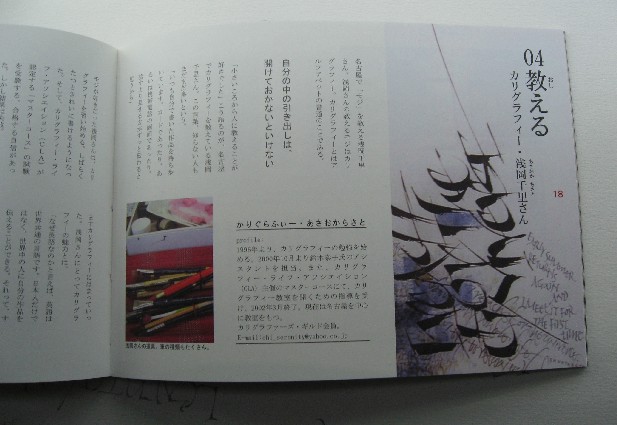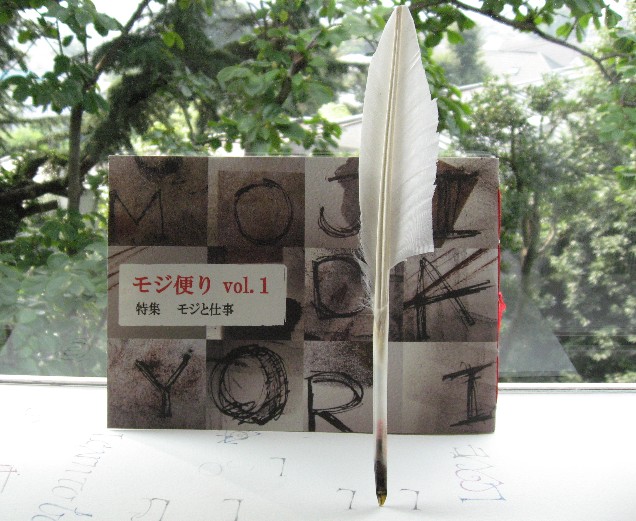
モジ便り
先週は、あるものを楽しみに待っていました。
それは「モジ便り」。
何か素敵な響きですね〜。
この本は、モジ好きの猿田彩さんという方が個人で作っている本なのです。文字に魅せられて、文字に関する仕事がしたい…という気持ちが「モジ便り」という形になったそうです。
表紙から中身まで、全て個人で取材、編集、デザイン、赤い糸で綴じたのもご本人!
輝かしい第1号の内容は、「書く」「売る」「デザインする」「「教える」の4つの枠を、仕事という視点でインタヴューを行った記事が載って
います。
文字好きなら興味深々の内容が並んでいます。
猿田さん自身が、いかに文字に対して愛情を感じているのかがわかる手作り本です。
今回は、カリ人浅岡千里さんの記事も載っています。
以前、mojitor-sさんが紹介されていた方ですね。
様々な地域で文字に携わっている方の様子を知ることができて
興味深いです。
「モジ便り」はお取寄せで待っている感じ…。
届くまで楽しみ〜。届いたら、すぐに中身を「いただきます!」
「やっぱり、待っていた甲斐があった美味しさ」
読み終えた後は、お茶席ならば「結構なお手前でした…」満足感にお腹いっぱい、頭もいっぱい
です。堺さんなら…?「星3つです!」
原稿用紙
先日、御茶ノ水へ行った時に入ったお店に、いろいろな種類の原稿用紙が売られていました。
原稿用紙というと昔小学校の時に作文を書く時に使ったなぁ、と懐かしくなりました。でもよく見ると、いろいろな種類があって、こだわる人はきっと選んで使うんだろうなぁ、と興味深く物色しました。
自分の名前入りというオーダーも出来るようでした。それって小説家の人が注文するんでしょうねぇ。でも今時パソコンが主流でしょうから、手書きの人が使うこういう原稿用紙はあまり売れないのかもしれませんね。
なんだかとても書き味を試してみたくなって、ふふふ!買ってみましたよ〜。100枚入っていて800円。どんどん練習に使うには惜しくないお値段。
やはりこの原稿用紙のクリーム色には、ウォルナッツインクのセピア色が似合いますね。上部にある升目のない部分のスペースが使えます。本来は校正の書き込みに使うのかしらん?
私が購入したのは、舛屋という紙屋さんの満寿屋(ますや)というブランドのものでした。浅草にある明治15年創業のとても古いお店の様です。
満寿屋の原稿用紙
舛屋
HPによると、川端康成、司馬遼太郎、井上靖、大江健三郎、三島由紀夫、吉川英治、吉村昭、瀬戸内寂聴、浅田次郎、などなど・・・・・・・。日本を代表する様な作家たちが愛用しているとか。すごいですね。
「ペン先を傷めぬ柔らかなタッチ、ユニークな升目、邪魔にならない色合い」と書いてあります。きっと長く使っていくと他とは違う使いやすさや味わいがあるのでしょうね。
関東地区だけでなく、関西や北海道、九州など全国で取り扱っているようです。
スラスラ書いてみたい人には、最適かも。お試しあれ〜
DERWENT METALLIC
ダーウェントのドローイング用の色鉛筆は素敵です。
以前、神戸のSさんがイギリスで入手したというのを使わせて頂いたことがあります。それぞれの色についた名前も素敵な響きでした。
国内で手に入れるのは難しいのかもしれません。
先日、美篶堂のショップでダーウェントのメタリックカラーが単品で売って
いたので、買ってみました。セットだと12色あるらしいですが、ショップでは5〜6色が置いてありました。
メタリックというからには、やはり暗い色の紙に書くと発色がいいのかな?
と思い、黒い紙に書いてみました。
さすがに目だっていますね…。ウエットにもドライにも使えるので、
脇役でも活躍しそうです。光沢が強いし、色がきれいです。他の色も
欲しい…。
白い紙の上でも、きれいに発色しています。
書いた感触では、goldが他の色より硬い気がしました。他の色pink, blue, pewter, silverは柔らかく滑らかでした。ドローイング用らしいので、普通の水彩色鉛筆より書きやすいかもしれません。
green とかyellowもあるようなので、それも使ってみたいです。
試し書き、描き…。
難しいことを考えないで、手を動かしているのが一番楽しいですね…。
コラージュのその後
先日作ったコラージュ用の紙がついにバラバラの残骸になりました。ということは、何かが出来たということです。
ドローイングと言う名前のクラスですが、何かを写生すると言う様な内容では全然なく、実に創造性を広げてくれる素晴らしいクラスなのです。
今回も、本当に楽しい内容でした。
そして出来たのは今のところこれとこれ。
他のメンバーの方たちのも是非紹介したい位、とても完成度の高いものが出来上がりました。
これは白黒のみの方ですが、実はカラーのも作ったのです。
それはまたいつかご紹介するとして、これら白黒のものにもまだもう少し書き足す事も考えています。やめた方が良いかなぁ・・
一緒に参加しているmojitor-hさんはコラージュにトラウマがあるとおっしゃっていましたが、それを打ち破って、素敵なカードも作っていました。一見の価値ありです。
コラージュは薄い紙の方が適していると思っていましたが、そうでもないんですね。
厚紙だと貼ったところにすこし影ができて立体的になり、非常にいい感じです。
講師の羽賀洋子先生の絵本の原画も見せて頂きました。コラージュです。印刷にはない色とテクスチャーがきれいでしたよ。
次回は「スピードの違う様々な線を使って描く」という内容です。
面白そう!
色をまぜまぜ
子どもが絵画教室に通い始めました。先日「50色つくる」という課題をみんなでやってみたそうです。
その塗り塗りしたものを持ち帰ってきたのですが「50色なんてそんなにたくさん作れなかった」ということでがっかりしていました。
まあ似たような色もあるものの1ページ分は作ることができたし、よかったじゃないの、と慰めて。
色としては私好みの色なので「いい色だねえ、あらー、この色は大好き」とほめて、本人満足。
混色するのは難しいけれど、子どもも大人も楽しいですよね。この色とその色とでどんな色ができるかなあ?なんて試してみるのはいいもんです。色見本をきちんと整理しておくとよいのですが、なかなかできないままに日が過ぎていってしまいます。
昔Denys Knightのワークショップで作ったガッシュの混色見本は今でも重宝しています。このワークショップのときにNaples Yellowを知って、手持ちの色に片端から混ぜて試したことを思い出します。透明水彩での混ぜ混ぜも飽きずに続けられる作業です。
秋の夜長にゆっくりやってみたいのですが、夜は早く寝てしまうので・・・途中で起きようと目覚まし時計をセットしているのですが
気がつくといつも朝、なんですよねえ。
週末くらいは夜更かししてみようかな。
栗ばっかり!
秋になると栗に憧れます…。栗!栗!栗!
面倒くさがりな私は栗剥きは苦手…というか、手は出しません。
だから、和菓子屋さんで剥かれた栗が形になっているのを見ると
嬉しくなり、買ってしまいます。
大福なんかは、秋の名月をお菓子の中に隠してあるみたいで、
栗が顔を出すと幸せな気持ちになります。くり〜。
まずは、「たねや」さん。一口サイズの上品な品揃い…。
白いまん丸したのは、「近江栗大福」(3個入り630円)。ど〜んと大きな栗が!存在感ありありです。周りのお餅も嬉しくなるぐらい美味しい!
茶巾しぼりの形をしたかわいいのが、期間限定?「さいぎぼく」(1個315円)です。こちらは少々高級な価格ですが、蒸されてまっとり(まったりとはちと違います)した口あたりが〜顔がほころびます。
昨日は、白山でデッサンのクラスがあったので、おやつにと
お取寄せした「栗抹茶大福」を持参。抹茶の香りがする餡で包まれた栗がここにいます〜。
伊藤久右衛門http://www.rakuten.co.jp/itohkyuemon/
Mさんが、自家製マロングラッセを持ってきてくれて、蜂蜜を使ってあるということで、何とも円やかに仕上がっていました。
あまりに魅力的だったので、写真撮るのを忘れてすぐに食べてしまいました〜しまった…。
栗の表示も楽しいですね…。
漢字だと視覚がすぐに味覚につながるようです。
左が、「たねや」さんの箱についていた「栗マーク」で
右が、「伊藤久右衛門」さんの箱についていた
「栗マーク」です。
タ〜ンと栗を頂いたあとは、残ったクロモジで記念の「栗マーク」
を描いて思い出に残します。
みなさんのお勧めの「栗お菓子」は何ですか?教えてくださいね。
2006年10月25日
平筆のイラスト
先日、折り形の本をアメリカの友人に送ったところ、お礼のカードと手紙が届きました。
折形レッスン―美しい日本の包み方内容は日本語で書いてありますが、折り線の種類と意味さえわかれば、器用な人なのできっと大丈夫だろうと、メモ書きだけ入れて送りました。
返事には、大丈夫だったと、書いてありました。さすがです。
お礼の手紙とカードは、得意の平筆によって花の絵が書いてありました。きれいですねー。どうやって平筆を使ったのか知りたいものです。花びらは平らに平筆を置いて、内側へシュッとかすれた線を出して書いているだけかもしれません。 今度試してみましょうね。
さて、お礼にということで彼女が取ったベティロークというカナダ人のワークショップのテキストが入っていました。私もアメリカにいる時に何度か彼女のクラスを取りましたが、平筆のマスターです。いろいろなアイデアと形がダントツに面白いのです。
特にこの部分、ハロウィーンのジャック-オ-ランタンとクモとタコみたいなゴーストが可愛いでしょう!?
ますますバージョンアップしていて、楽しくなります。
きっと描けないものなどないでしょうね〜〜。
よく見たら上の部分にA〜Zまで書いてありました。
これでけでもなーんて素敵!
2006年10月22日
韓国和紙
サキチさんに韓国和紙をお土産に頂きました。
韓国なので和紙ではなく韓紙と言うのだそうです。印刷(版画のような感じ)ですが、風合いがあってとてもイイ感じなのです。
残念ながら私はハングルは読めないので、この方向で合っているかどうかもわかりません。不思議な記号という感じですね。
紙は中国で発明されて朝鮮半島を経て日本へ渡ってきたのでしょうから、同じ様な紙があって当然なのですが、とても新鮮な印象です。
日本橋にある小津和紙には、韓国楮の和紙がたくさんありました。よく探せばきっと面白い紙がありそうです。日本のものとの違いもあるのでしょうね・・・
そのまま何かに使うチャンスもなく、眠っています。いつか何かに使わなければ!
これは、以前アメリカの友人からもらったカード。和紙が表紙に使われています。折り紙のたたみ方をしたシンプルなカードです。
ところでこのカードに書いてある文字の形、とても面白いですよね。もう10年以上も前なのでよく覚えていませんが、たしかborn lettersと言ってたような・・・。ホネホネっぽいから?